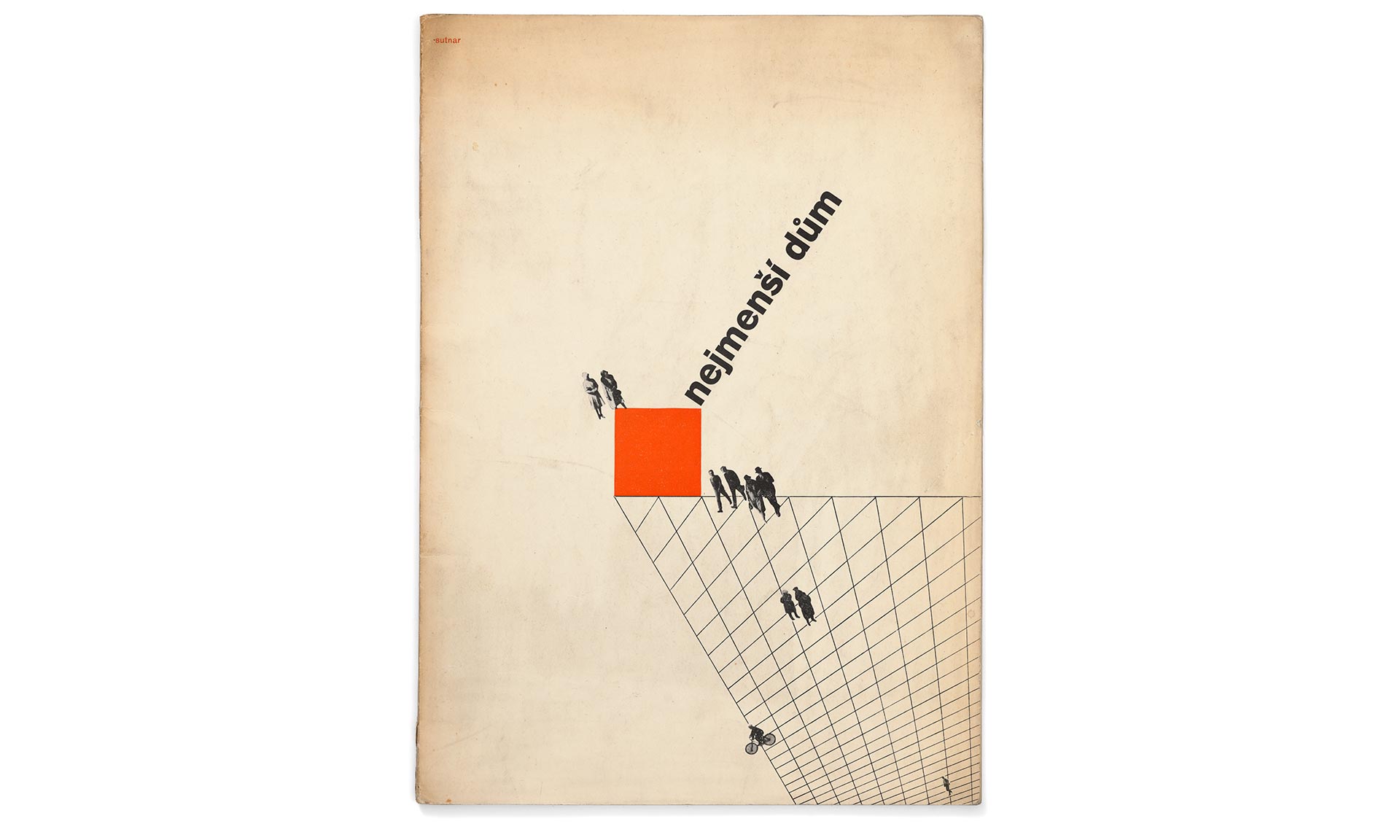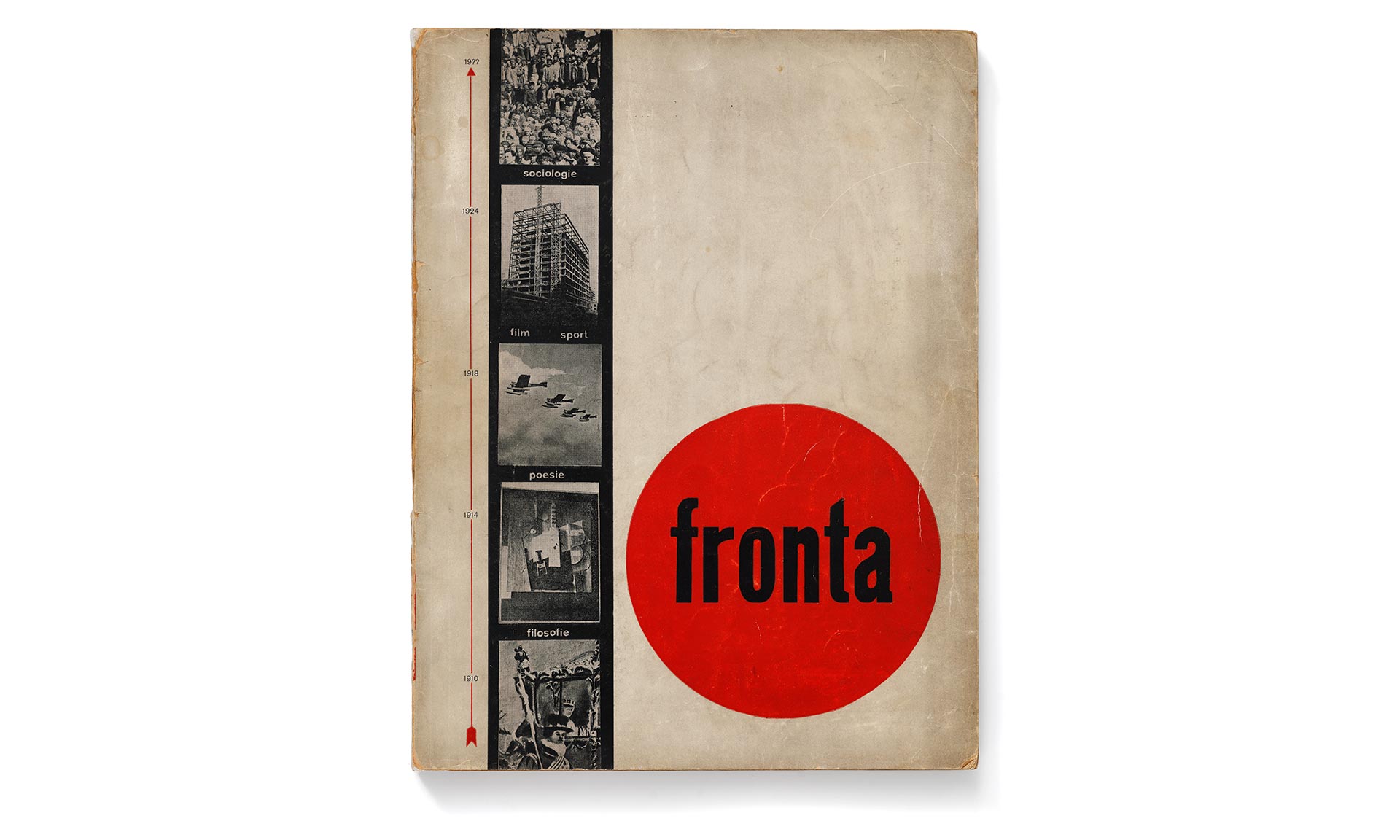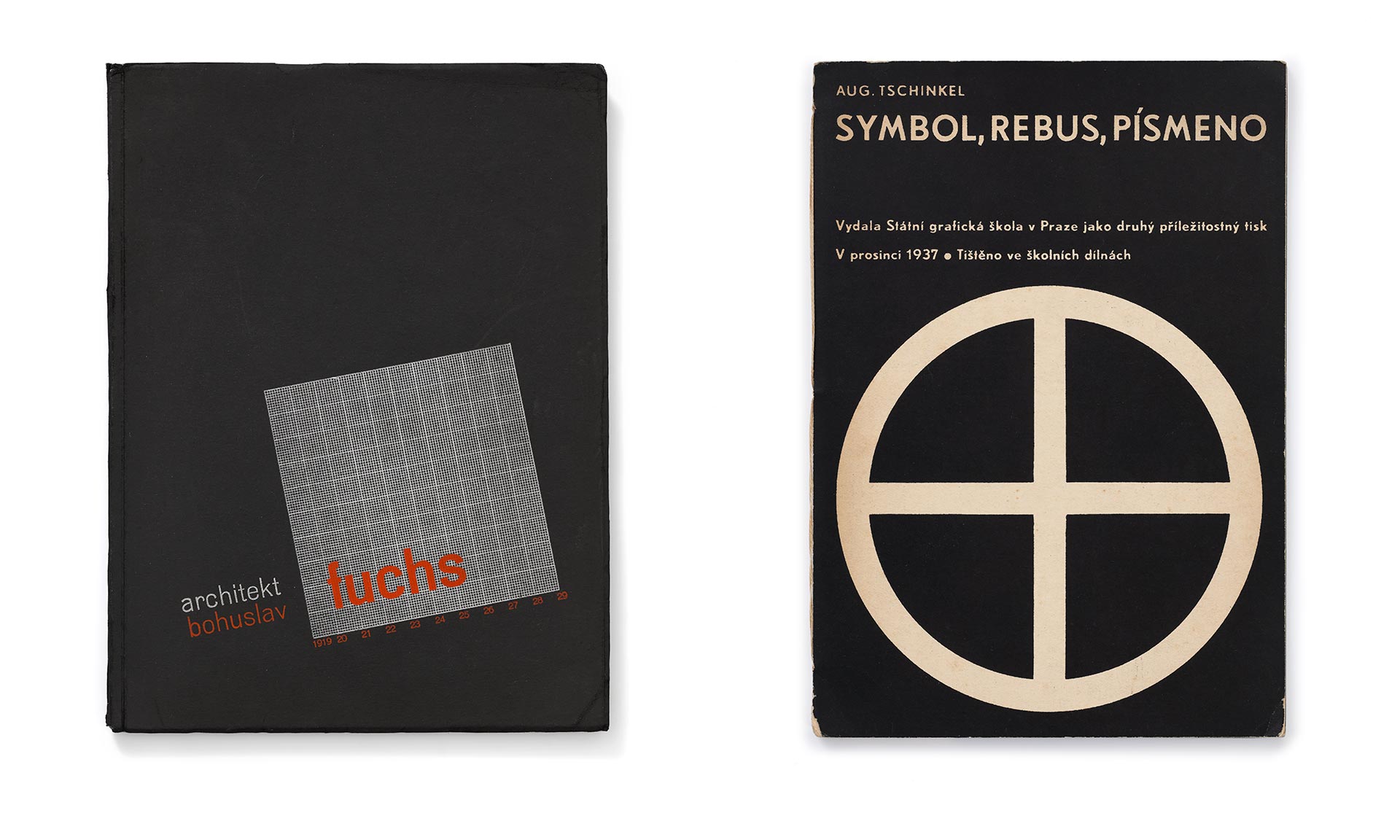
V pražské Galerii UM byla zahájena výstava Abcd s podtitulem Česká funkcionalistická typografie ze sbírky Karla Císaře a studie k reliéfům 2016-2017 Floriana Pumhösla. Až do 2. prosince je možné seznámit se nejvýznamnějšími ukázkami ze sbírky funkcionalistické typografie filozofa, teoretika umění Karla Císaře, který je zároveň pedagogem na UMPRUM.
„Výstava navazuje na skupinovou expozici Obrazy a předobrazy, kterou jsem před deseti lety připravil pro Galerii hlavního města Prahy v prostoru Městské knihovny. Zatímco ale tehdy jsem vztahoval díla čtyř současných zahraničních umělců ke středoevropskému meziválečnému výstavnictví, funkcionalistickému sklářství a surrealistické typografii, v Galerii UM nyní konfrontuji ukázky z vlastní sbírky české funkcionalistické typografie se studiemi k reliéfům 2016/2017 od rakouského umělce Floriana Pumhösla, jednoho z účastníků někdejší přehlídky,“ říká Karel Císař.
„Florian Pumhösl vyšel z redukce funkcionalistické typografie v geometrii kreseb na skle, které byly součástí výstavy documenta 12 v Kasselu v roce 2007. V expozici společně s kresbami byly proto vystaveny i plexisklové boxy s ukázkami časopisu Front. Srovnáme-li jeho kresby z jejich grafickými zdroji, zjistíme, že neodkazují ani tak k textu či ilustraci, ale především k principům rozmístění optických jednotek na stránce. Zdvojená linie černých linek odkazuje k prázdnu, jež oddělovalo sekvenčně snímané záběry letu parašutistů ve zvláštním čísle časopisu Front z roku 1943. Podobně je tomu i v případě konstruktivistické obálky českého typografa Zdeňka Rossmanna, jejíž ukázku Pumhösl užil ve svém reliéfu z roku 2010: hladká plocha obálky představuje nejekonomičtější formu sdělení, kdy je naše pozornost vedena rychle a účelně,“ dodávají zástupci UMPRUM k druhé části výstavy.